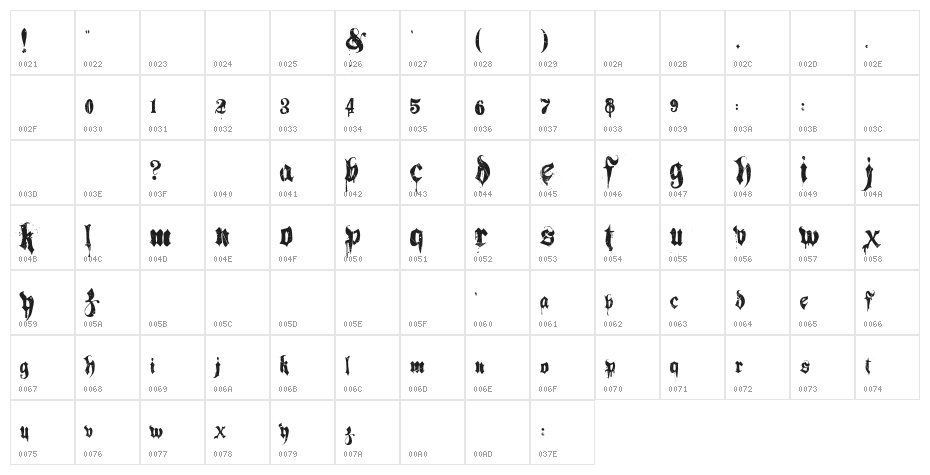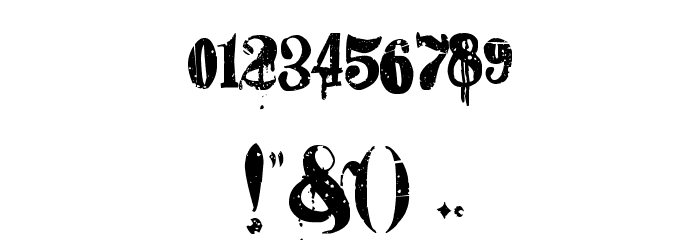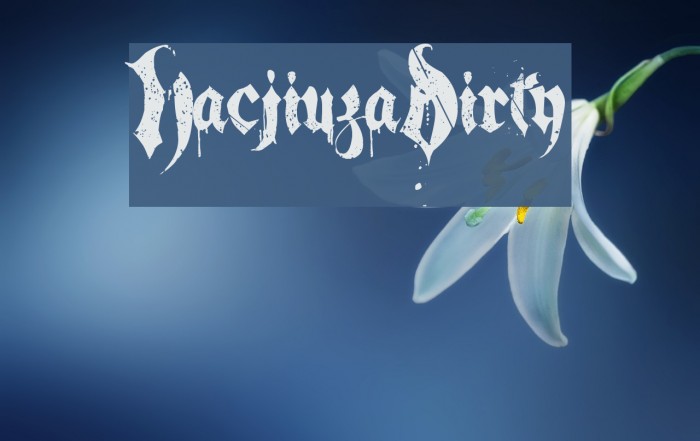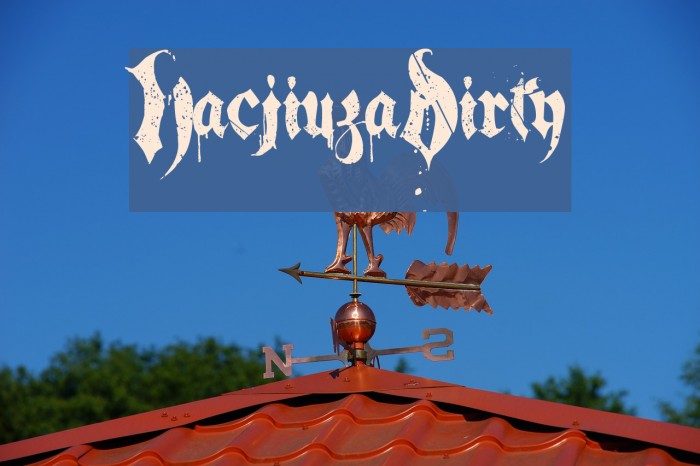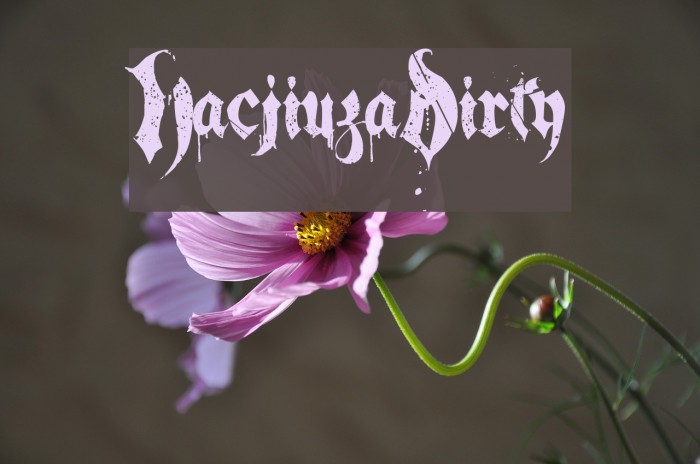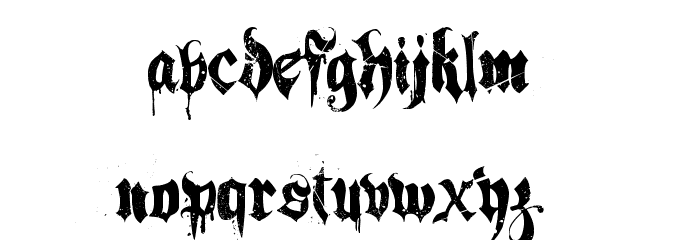
HacjiuzaDirty Font
✎ Gothic
| Progetti proposti | Ideal for posters, album covers, themed events, or any project needing a dramatic, historical touch. |